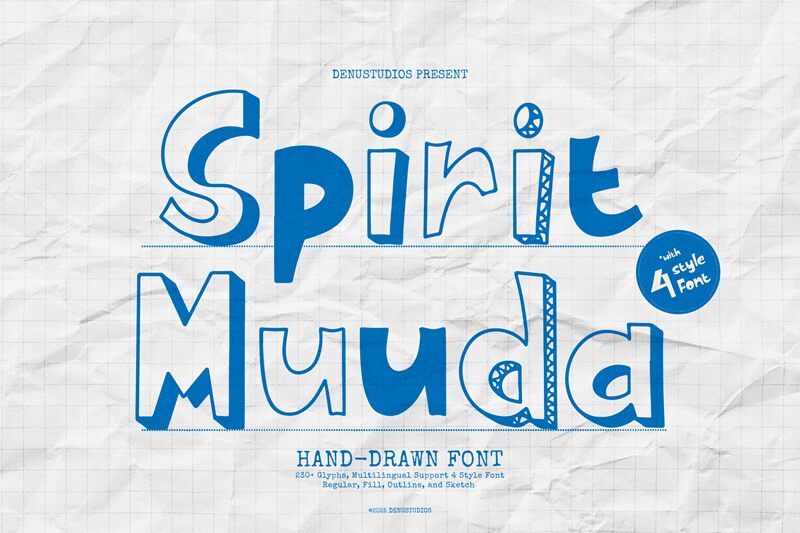
Spirit Muuda Fill, da Denustudios, é uma fonte display gratuita com um estilo cartoon saltitante e desenhado à mão. As letras apresentam formas suaves e volumosas com bordas levemente irregulares, conferindo à fonte uma personalidade alegre e um tanto travessa, em vez de um aspecto rígido ou puramente geométrico.
É perfeita para embalagens vibrantes, capas de livros infantis, cartazes de festas, branding criativo ou títulos para redes sociais, onde a simpatia vale mais do que o polimento técnico. Por ser uma fonte gratuita, é ideal para manchetes curtas, gráficos tipo adesivo ou rascunhos de logos, pois as formas encorpadas e o ritmo irregular trazem uma energia comunicativa e viva até para poucas palavras.